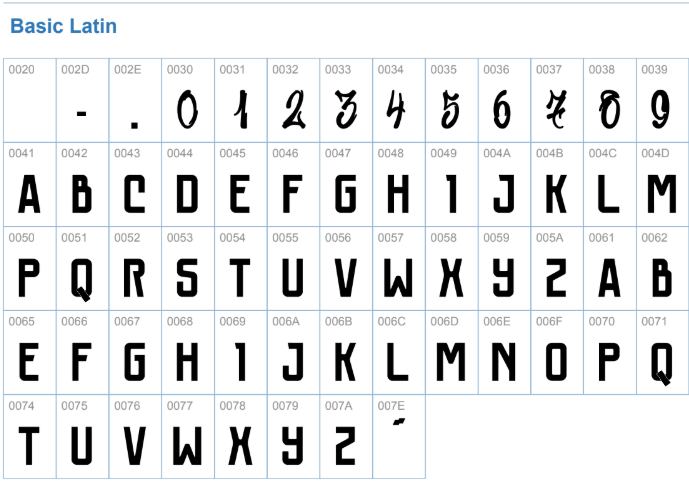
A temporada 2025 mal começou e o Botafogo já deu o que falar com seus novos uniformes. Enquanto as camisas tradicionais mantêm a história, é no “Quarto Kit” (ou Cuarta) que o design realmente brilha e ousa. Este ano, a tipografia escolhida para os nomes e números desta camisa especial roubou a cena.
- Nome da Fonte: Botafogo Cuarta 2025 (Adaptada)
- Uso Ideal: Perfeita para mockups de uniformes, artes para redes sociais, layouts de sites, personalização de presentes e projetos de design gráfico que exigem a identidade visual do Botafogo em 2025.
Diferente das fontes clássicas que vemos de gigantes como Nike ou Adidas, a tipografia da camisa 4 do Botafogo 2025 foi desenhada para transmitir energia e modernidade.
Ela possui linhas dinâmicas, com cantos levemente angulares que dão uma sensação de movimento e velocidade. Não é uma fonte robusta demais, mas tem presença suficiente para se destacar no tecido, garantindo excelente legibilidade tanto na TV quanto no estádio. É uma fonte que equilibra a tradição do clube com uma pegada visual agressiva e contemporânea, alinhada com a proposta ousada dos uniformes cuarta.